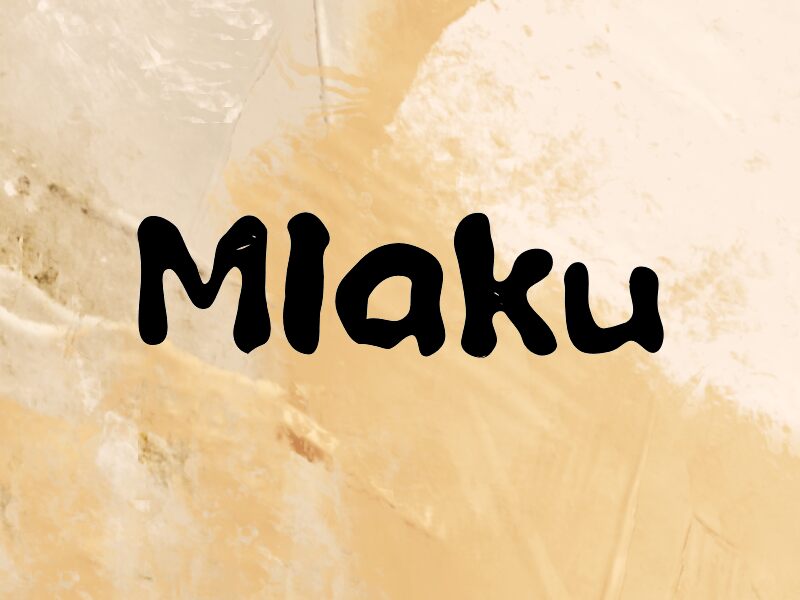
Mlaku
Mlaku di Wep è un font display gratuito in stile cartoon con un tocco giocoso e modellato a mano. Le lettere appaiono morbide, spesse e leggermente irregolari, con angoli arrotondati, curve sinuose e piccole tacche che rendono l'intero design spiritoso invece che impostato.
È perfetto per copertine di libri per bambini, packaging di snack, adesivi, branding creativo e post sui social dove un font gratuito standard sembrerebbe troppo rigido. Usalo per titoli brevi, schermate di presentazione o loghi quando vuoi che le lettere sembrino morbide e vivaci: le forme bulbose ripetute e il ritmo irregolare comunicano già tutto da soli.